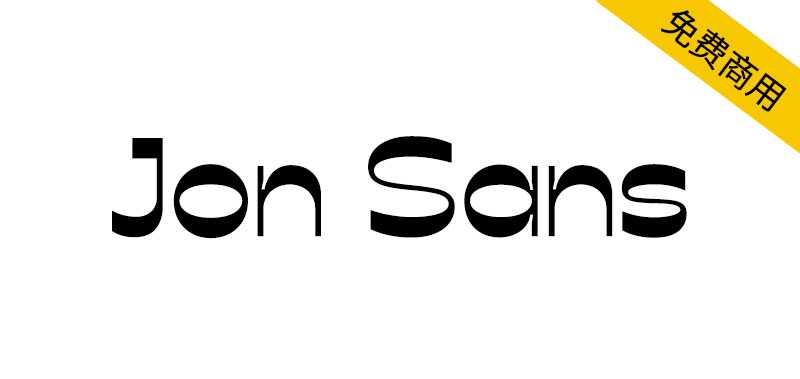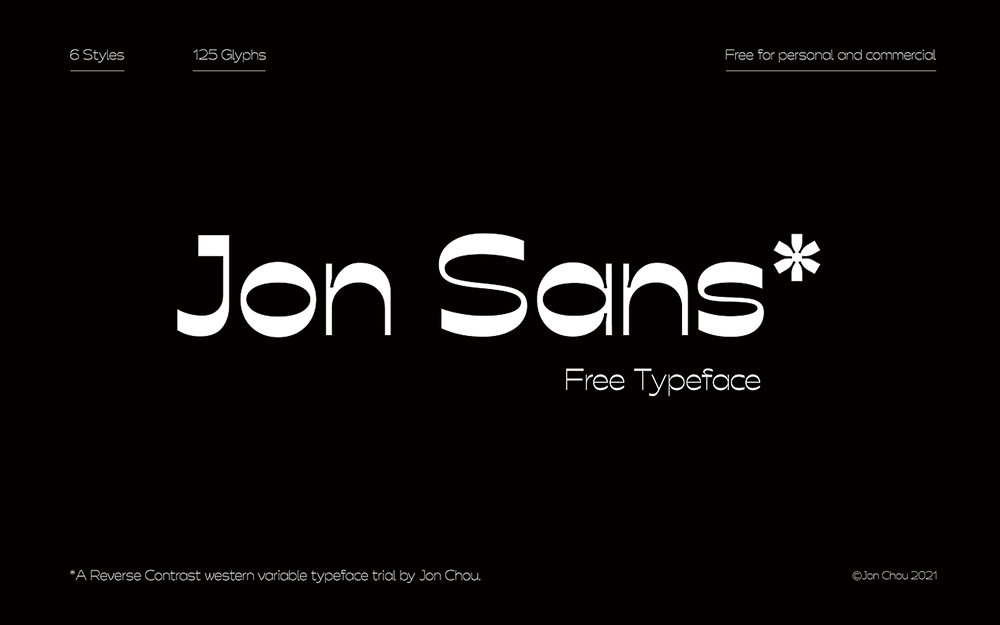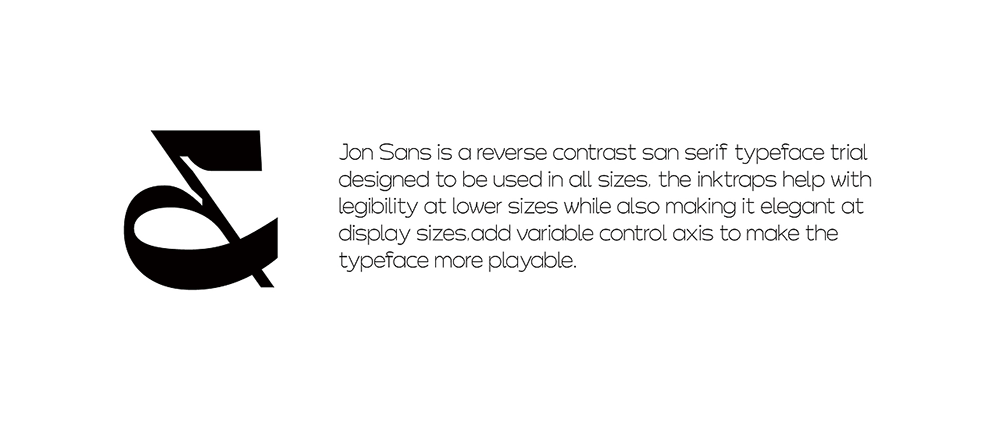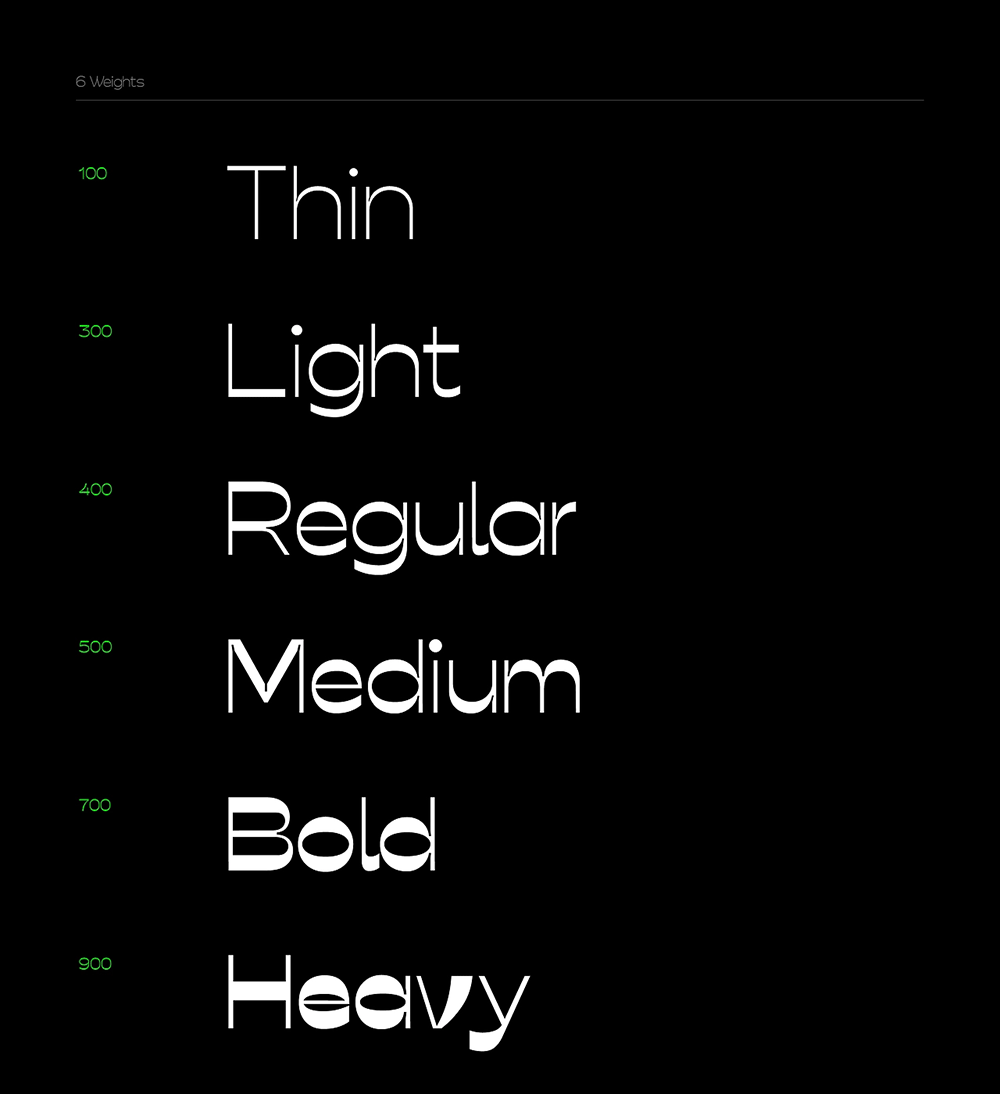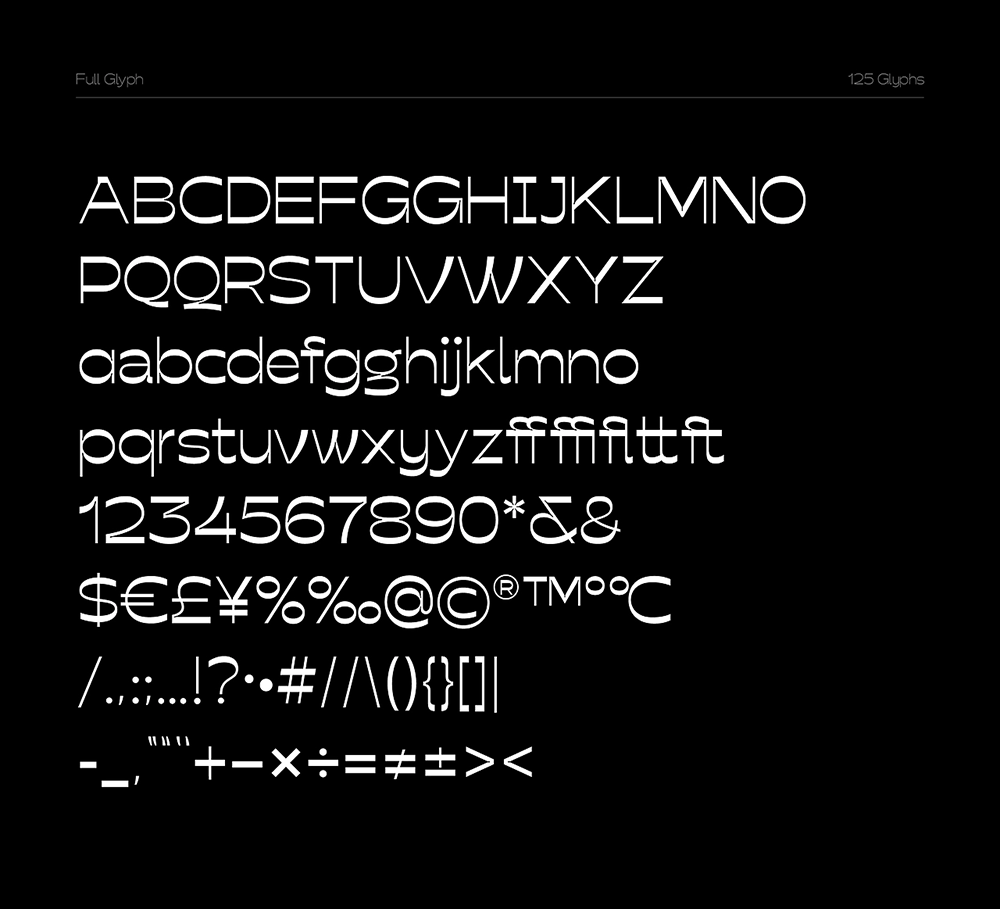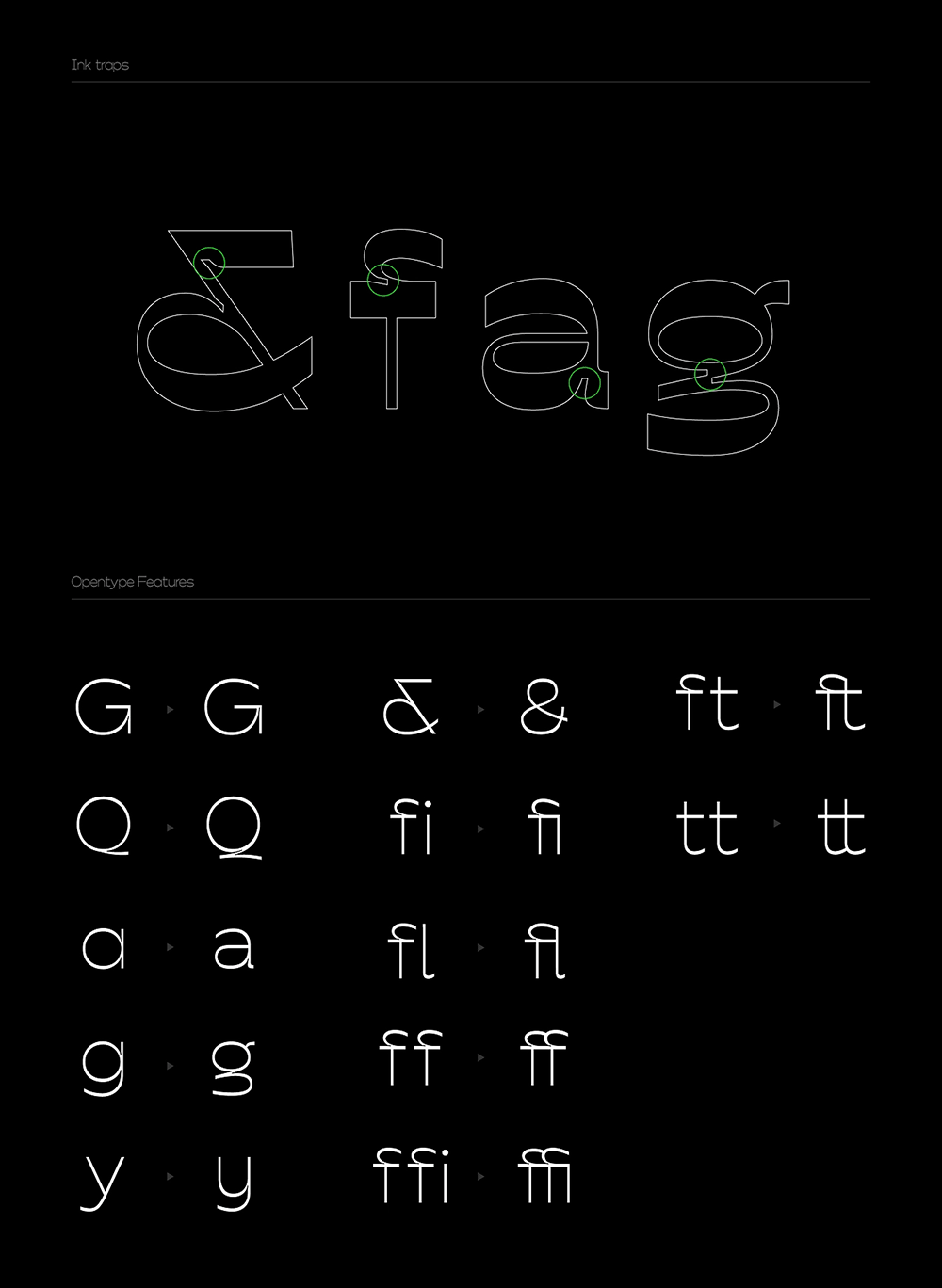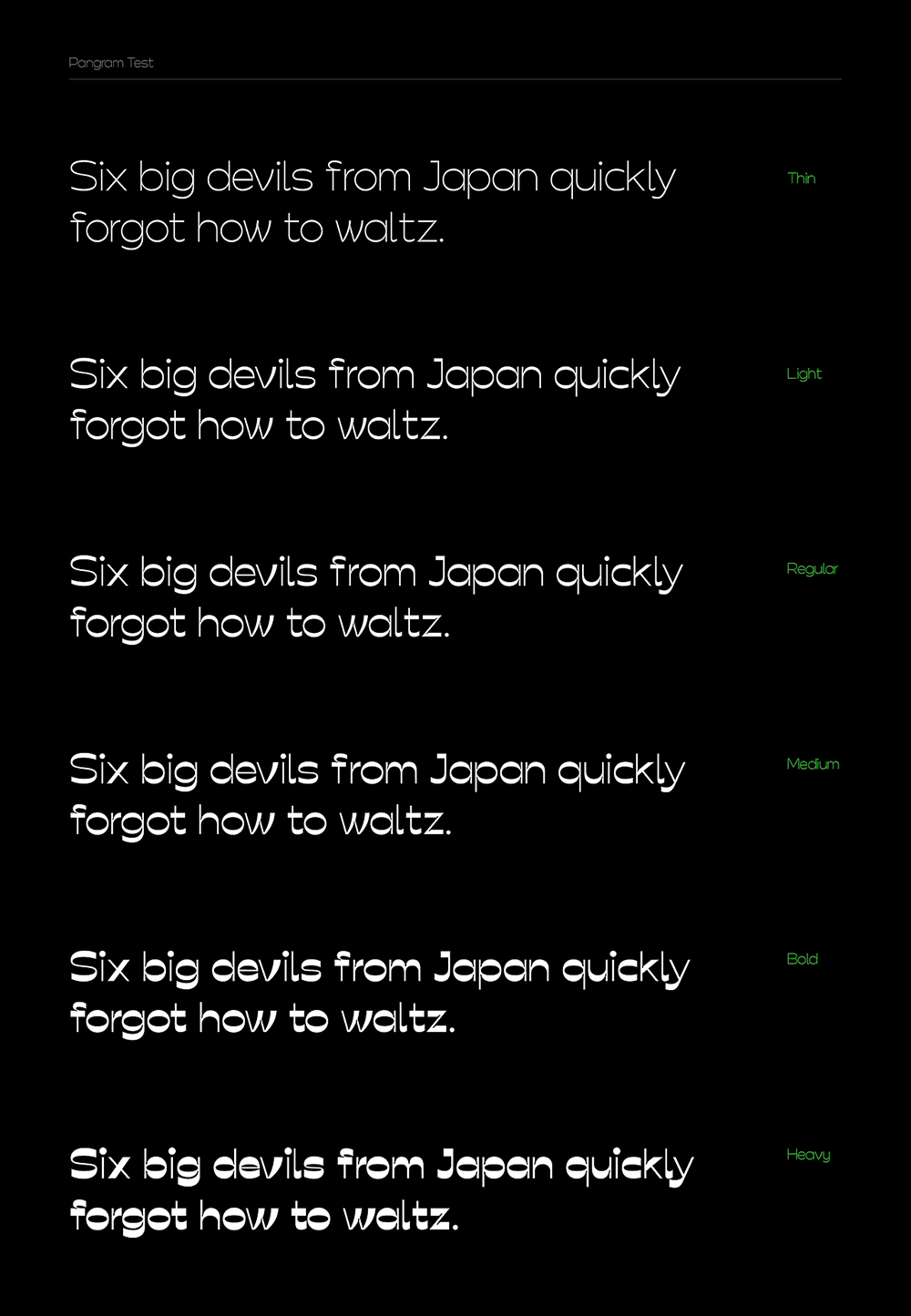
【Jon Sans】一套逆反差西文可变免费字体
Jon Sans是一套逆反差西文可变字体。西文逆反差字型(Reverse Contrast),结合“Ink Trap”(油墨扩张弥补)风格。内置六个字重,加入可变字重控制,满足不同应用场景。适合在一些酸性设计中使用。第一次做西文字体,不太成熟希望多多交流~个人和商业免费使用。有必要时记得作者署名哦!